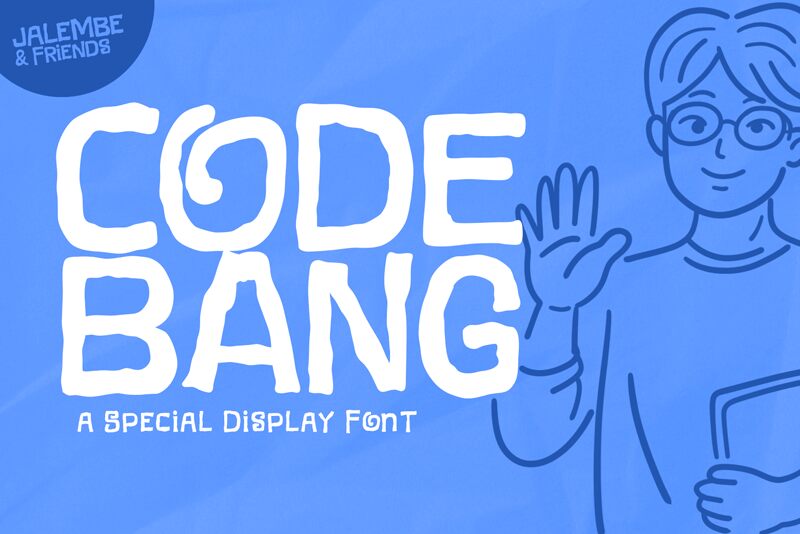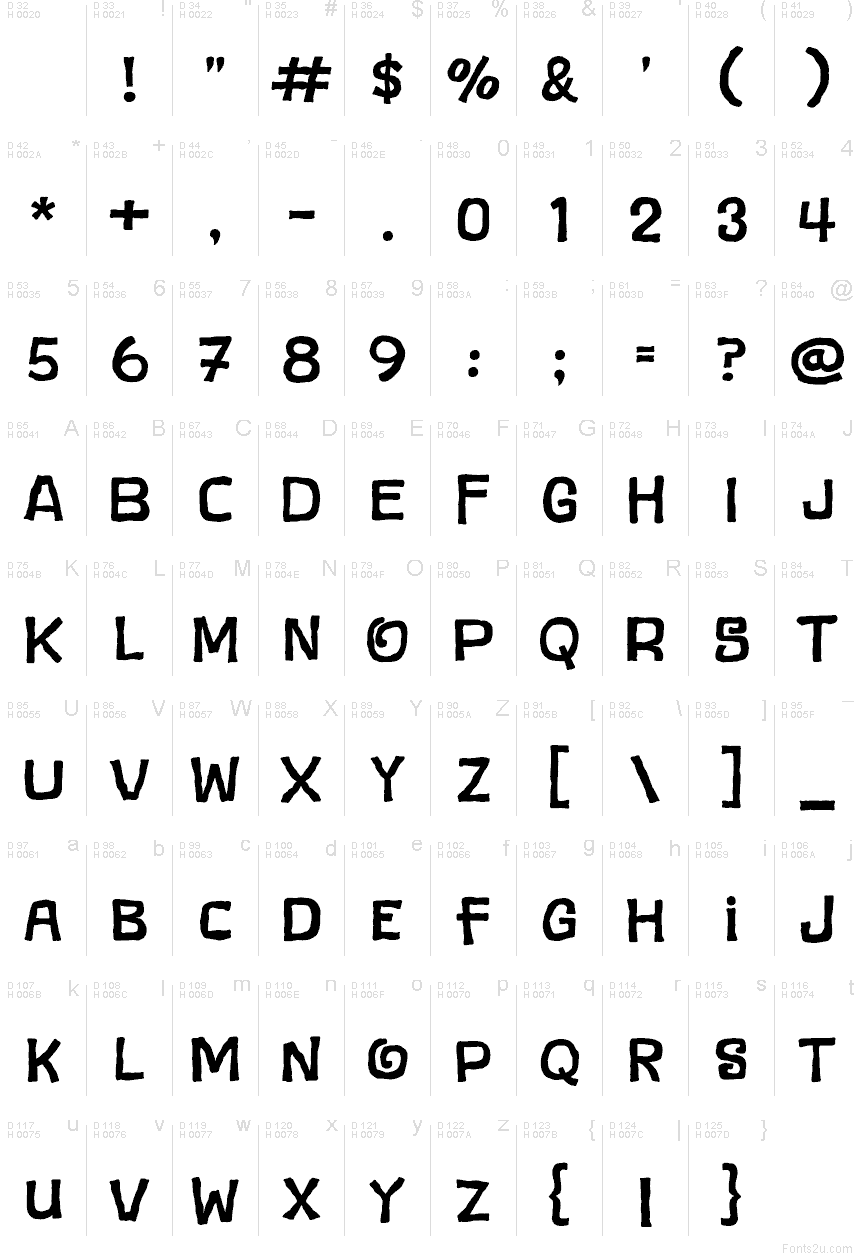
Code Bang
Code Bang от Khurasan & Jalembe - это мультяшный акцидентный шрифт с округлыми, неровными формами, создающий эффект нарисованного от руки текста. Его очертания колеблются между плавными кривыми и рублеными краями, а некоторые знаки повернуты внутрь, создавая причудливый, «скетчевый» ритм.
Code Bang отлично подходит для заголовков плакатов, обложек комиксов, детских проектов, игровой графики и брендинга в стиле наклеек, так как его формы выглядят непринужденно, не теряя при этом четкой структуры. Этот бесплатный шрифт также хорош для оформления упаковок, заголовков мероприятий и коротких логотипов, когда вам нужно, чтобы надпись выглядела нарисованной, а не строго геометрической.